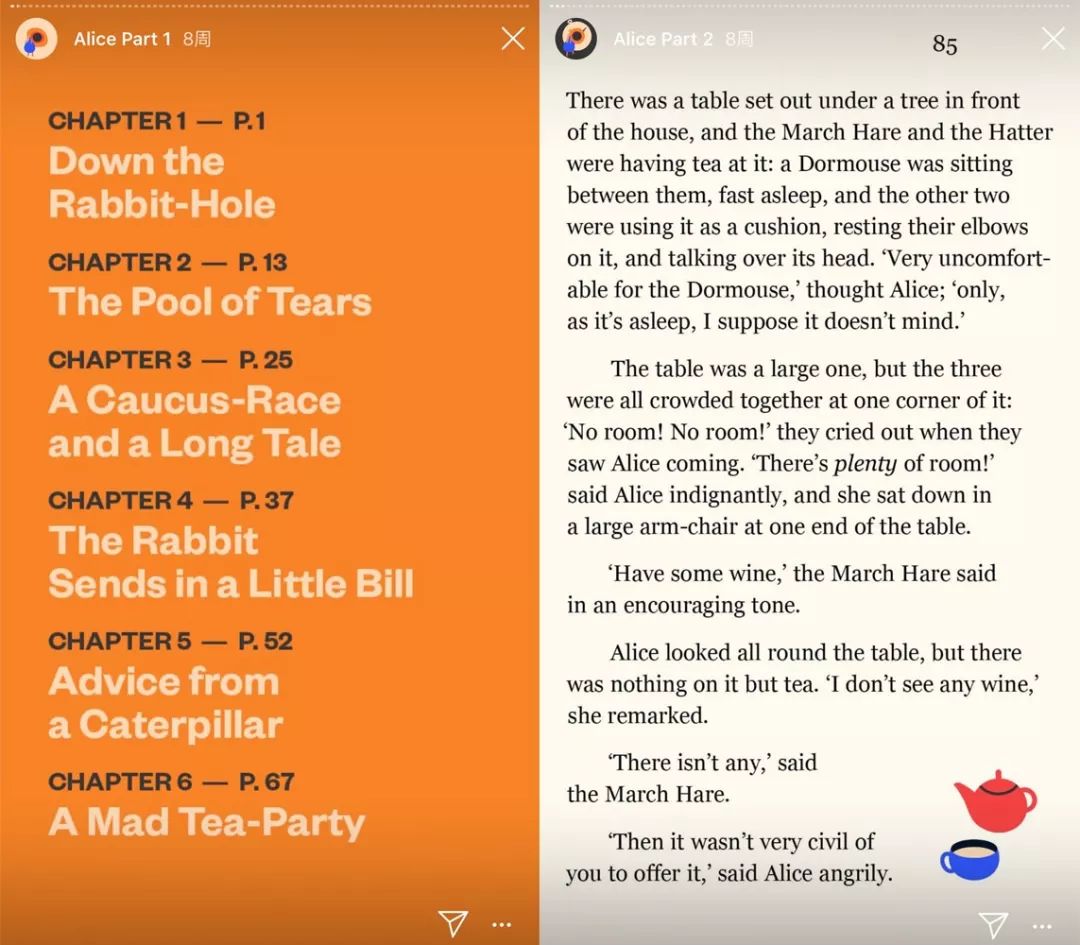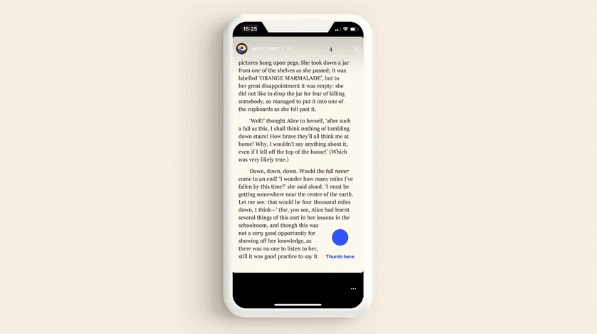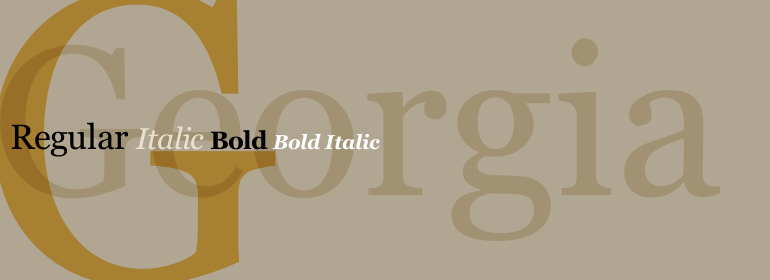
什么?那个网红INS能用来看书了,还是动的
一说到ins,柚子脑海里就浮现出各种高逼格(p过头)的网红照,可它现在居然还能看书了,这是要抢占kindle的市场吗?
No,其实这个是纽约图书馆(NYPL)和Instagram共同合作的“Insta Novels”项目,只要你关注@NYPL,就可以在它的主页上,看到又像视频又像动画的经典小说,第一部就是大名鼎鼎的《爱丽丝漫游仙境》。
该系列的插图由@Magoz设计,一层又一层的圆圈,好像真的跟随爱丽丝进入到那个神秘的仙境。
内文翻起来也很有意思,你可以将拇指放在屏幕上来暂停页面,抬起拇指来翻转页面,与此同时,右小角的元素也会跟着变化,有时候是茶壶、有时候是眼睛、有时候是扑克牌,就像动画片一样。
但说到底,做得再炫,它也是书,离不开文字。为了更易于阅读,Insta小说特意在暖白底色上,选择了Georgia字体。
这个字体有多厉害呢?只要随便翻开一本书,或随便打开一个网站,都有可能看到它,是由世界级字型大师Matthew Carter,专为屏幕显示设计的。
它最大的特点就是小字号也能清晰辨认,妈妈再也不会戴着眼镜看了(也看不懂)。
如果你读到中间,还会发现一些惊喜,比如有的段落会弯弯曲曲地弹出,就像爱丽丝跟着毛毛虫跳舞一样(排版限制了我的想象力)。
还有,Gilman的短篇小说《黄色墙纸》,也在insta上线了,@buck_design负责插图。
另一部即将上线的,是Kafka的小说《变形记》,@cesarpelizer负责插图。
如果以后都这么看书,我可以瞬间读完所有名著,因为太轻松了,不过,先得把英语学好。